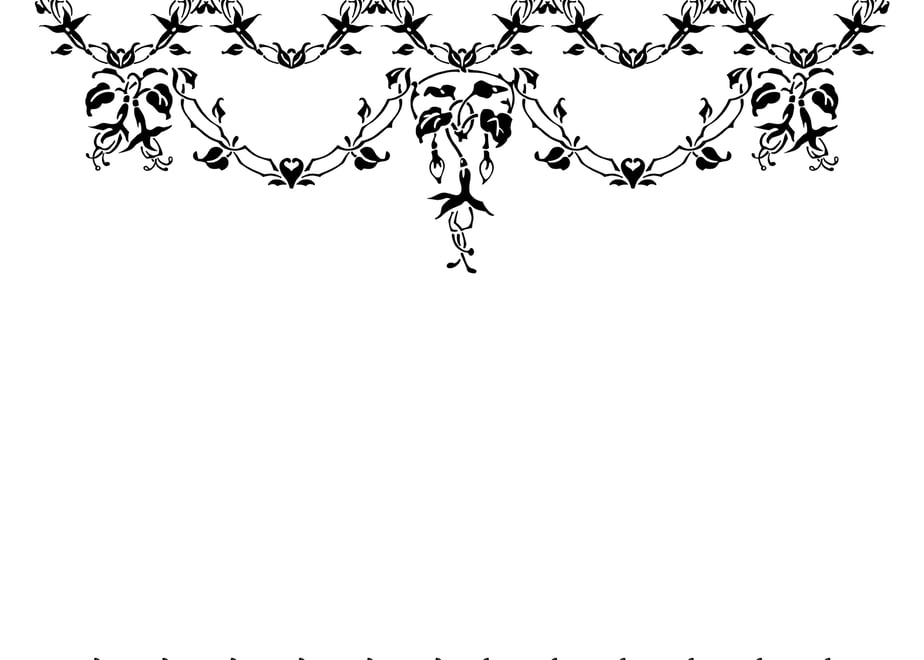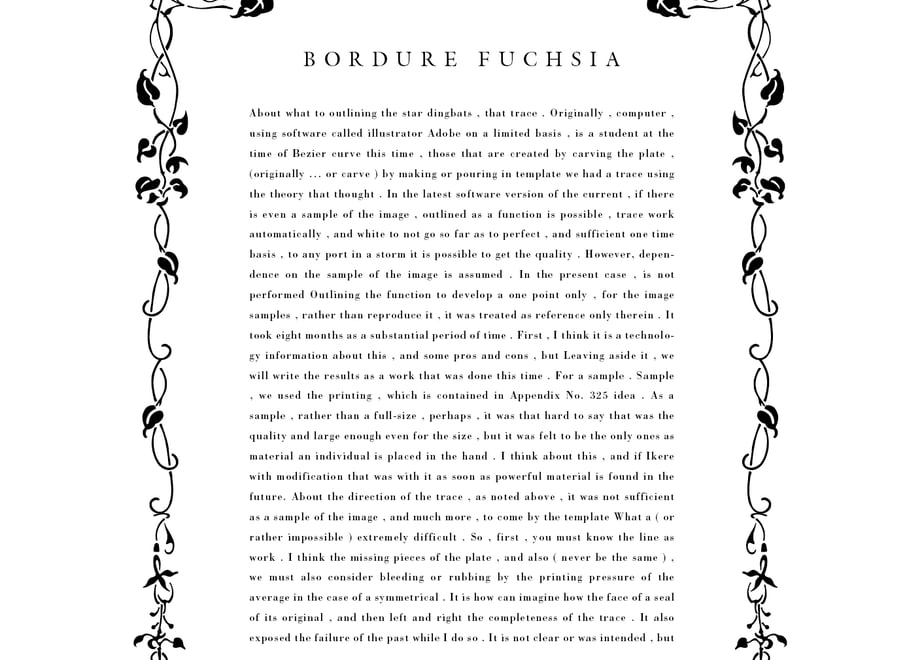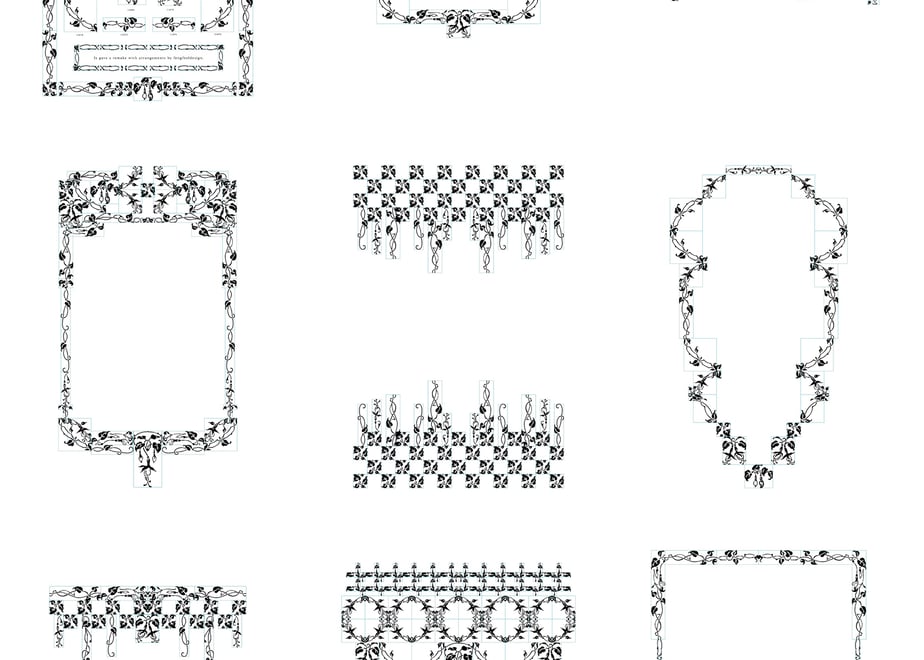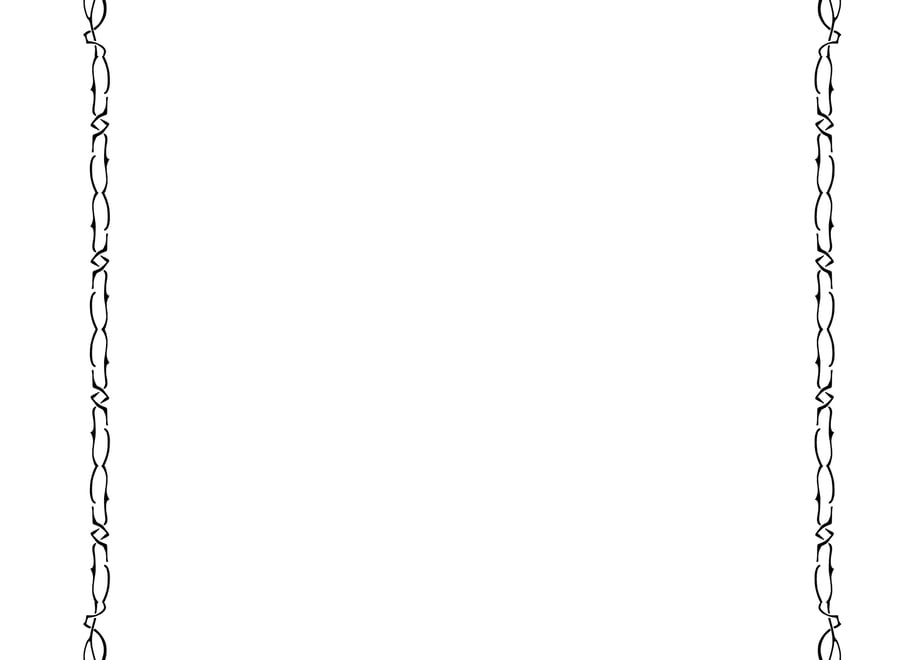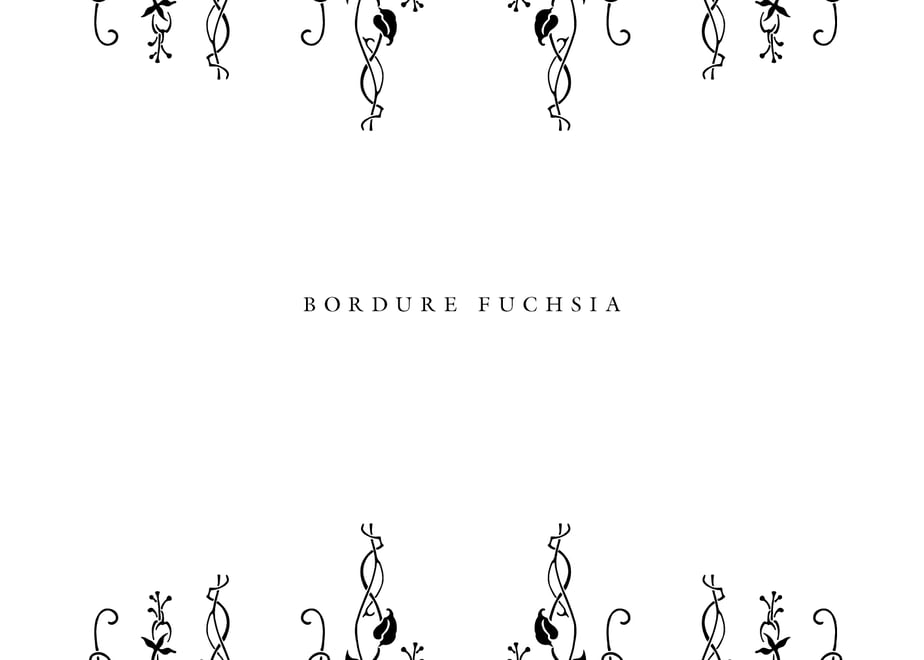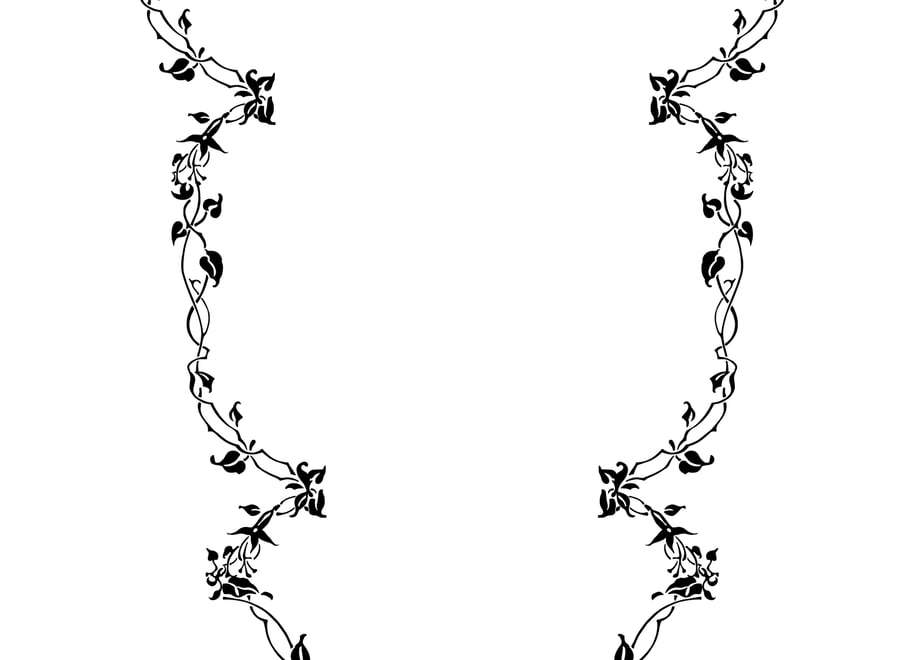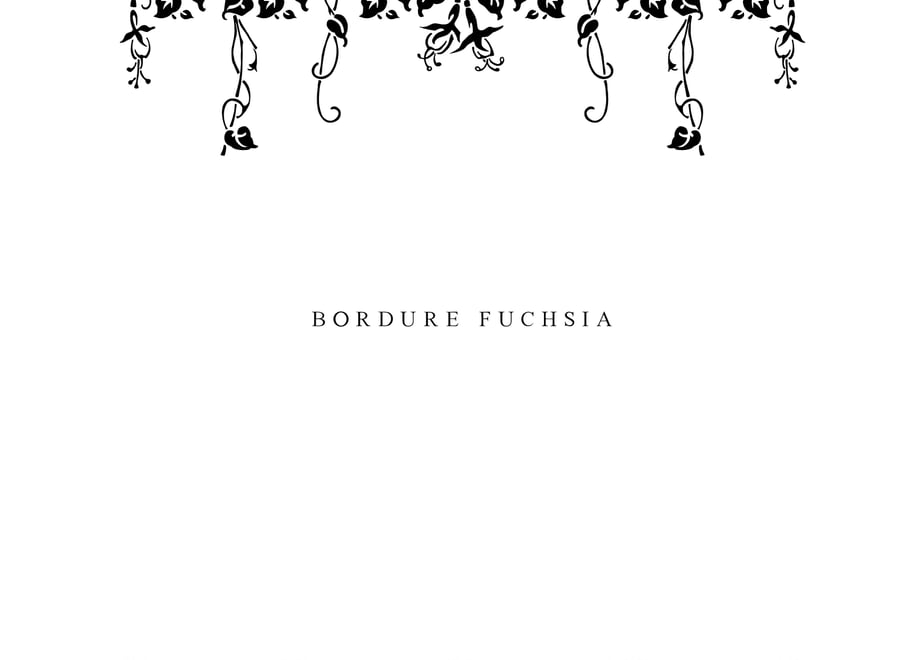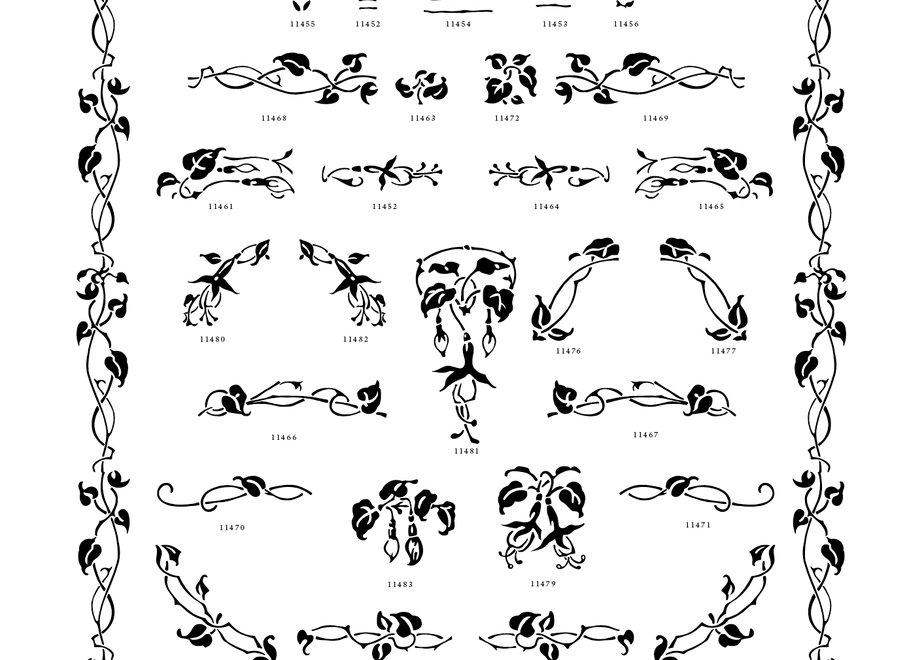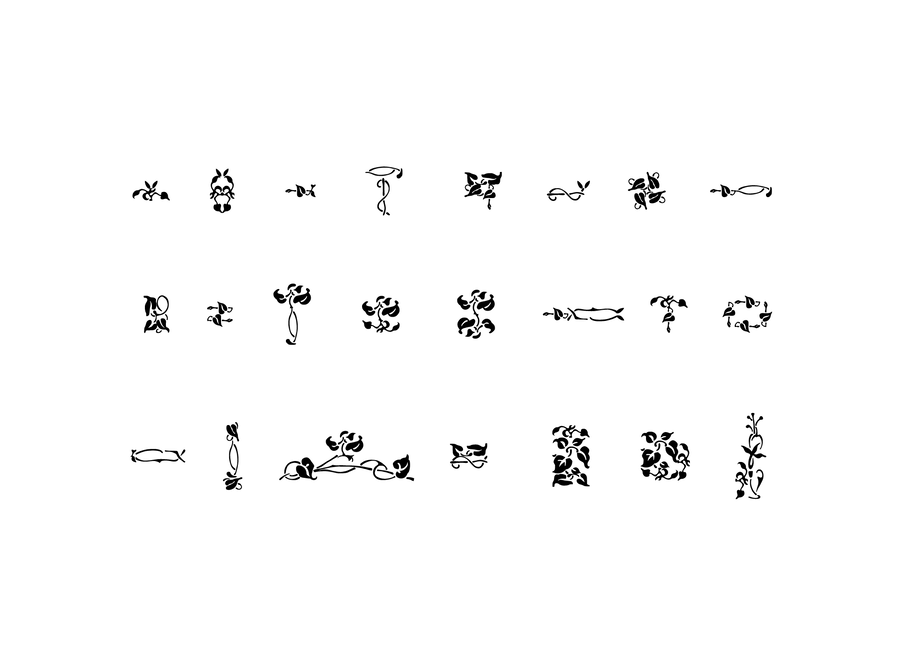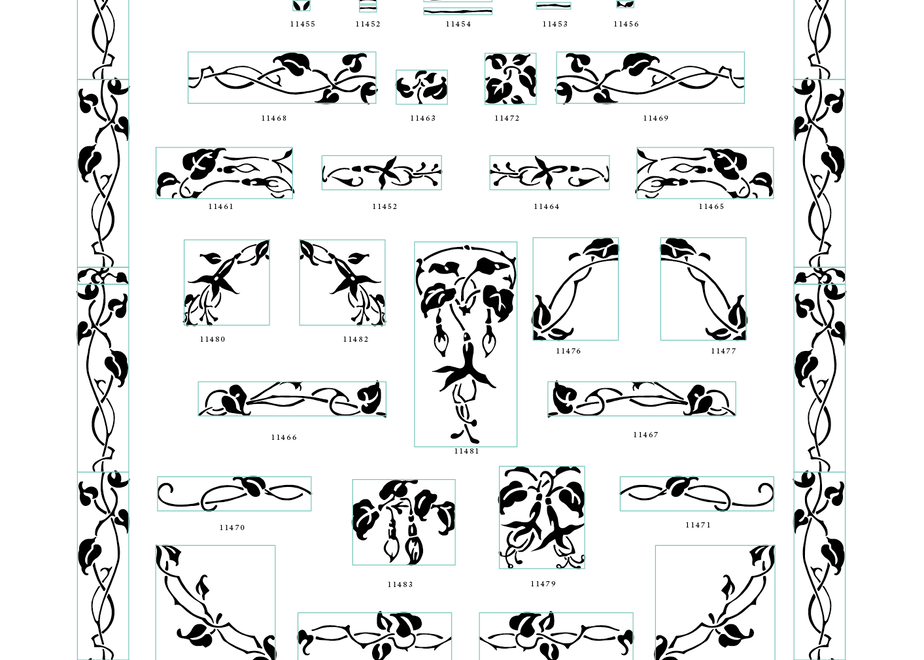
装飾活字:BORDURE FUCHSIA F
フクシアの花をモチーフに制作された装飾活字を、現代のデザイン環境で利用できるよう再構築したデータパッケージです。
38種類の装飾ユニットを自由に組み合わせることで、装飾罫線やフレーム、パターンなどを制作することができます。
本商品は、ドイツで活版印刷職人として活動されている方からご提供いただいた資料をもとに制作しました。
制作にあたってはAdobe Illustrator上で一点ずつアウトライン化を行い、オリジナル資料の構造を分析したうえでユニットを再設計しています。
また、オリジナル資料では一部ディテールと版面比率のバランスに課題が見られたため、ユニット内に収まるよう細部を調整しながら手作業で修正を行い、実用性と再現性を両立したデータとして再構築しています。
BORDURE FUCHSIA Fは、フクシアの花をモチーフとして設計された装飾活字です。
四角形のユニットを基準として構成されているため、組み合わせによって様々な装飾罫線やフレームを制作することができます。